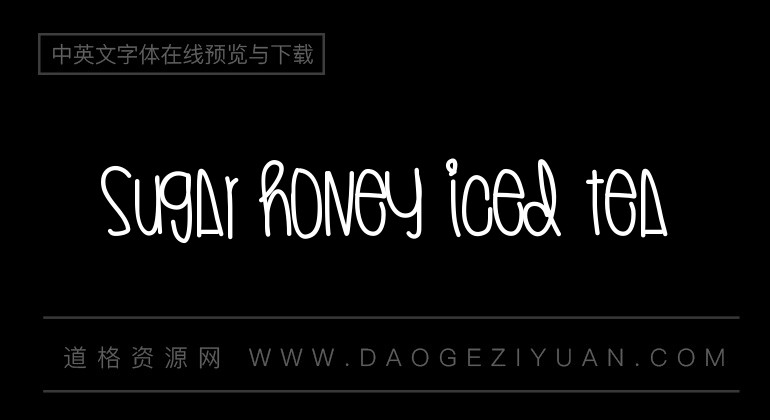
Sugar Honey Iced Tea
Sugar Honey Iced Tea 字体是一种轻松、可爱的字体,它具有柔和的曲线和深邃的色彩,可以带来温暖的感觉。它的字形精致而又有趣,可以用于各种场景,如海报、卡片、礼品、婚礼和其他社交活动。它的简单、可爱的外观可以帮助你在设计中脱颖而出,给人们留下深刻的印象。
Sugar Honey Iced Tea是一款非常不错的手写艺术字体,具有很好的视觉感,适合于文化类的宣传设计、商业类品牌的广告和产品包装设计以及个性化文字排版等较多场景。